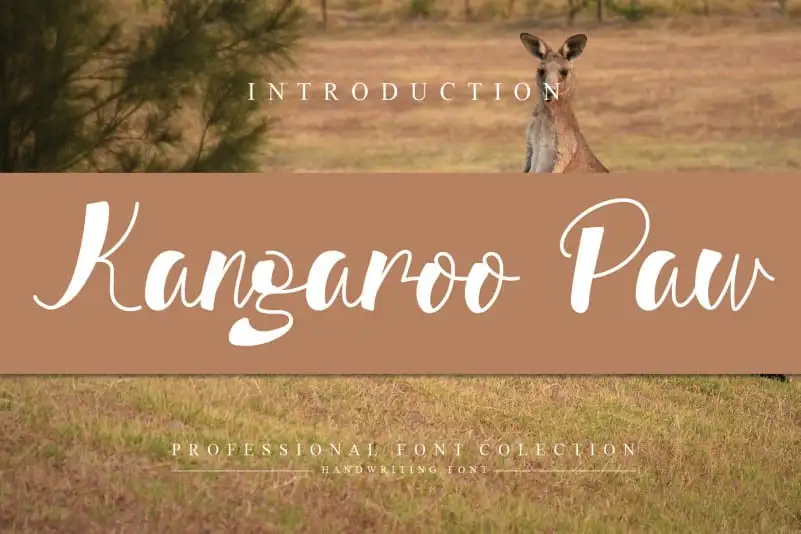
Kangaroo Paw Script Font – Fonte Grátis
Kangaroo Paw Script Font
A Kangaroo Paw Script Font é uma elegante e trendy fonte escrita a mão que elevará seus designs ao nível mais alto. Com uma originalidade incrível, esta fonte oferece um toque sofisticado e divertido para qualquer projeto. Perfeita tanto para gráficos de marca quanto para elementos de design minimalistas, ela traz um charme único que certamente dará vida à sua próxima criação visual. Seja você um designer de branding ou uma artista gráfica experiente, a Kangaroo Paw Script Font é definitivamente o tipo de fonte que irá tornar seu trabalho ainda mais especial.